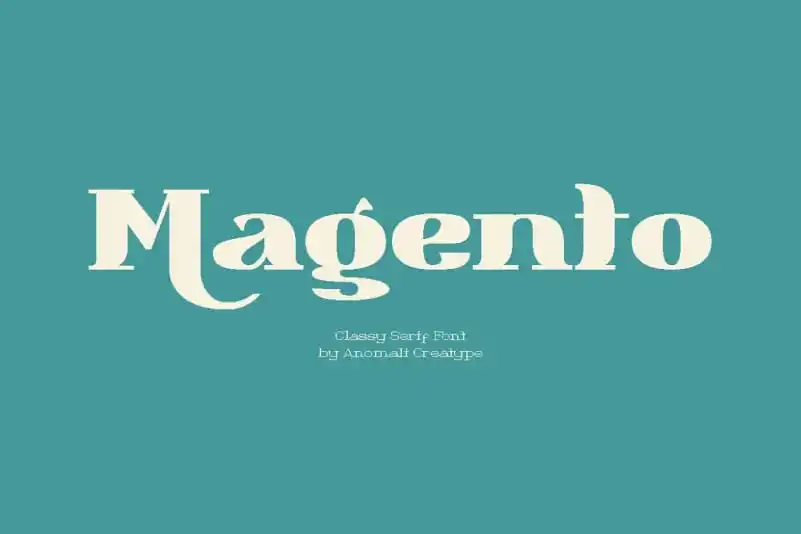
Esta é uma fonte Serif que traz um toque retro com nuances modernas, apresentando 8 versões diferentes. Foi projetada e compartilhada pela equipe Anomali, destinando-se a ajudar na criação de design para projetos de projeto do meio dos anos 60 ou 70. Suas linhas estilizadas são perfeitas para dar um toque sofisticado em projetos de layout que exigem elegância e profissionalismo. Seja você designer de moda, publicitário ou criativo com projetos legais, essa fonte será uma ótima opção para dar um toque único ao seu trabalho. Experimente agora para adicionar um sabor vintage a seus designs.